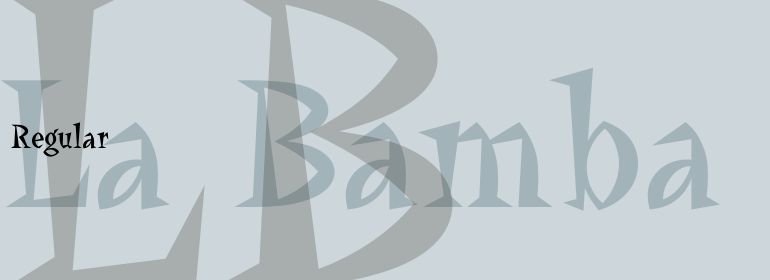
La Bamba™
La Bamba是英国设计师David Quay的作品,它深受20世纪50年代风格的影响。它具有完整的大写字母和小写字母以及一组装饰性的大写字母,以增加多样性。La Bamba是一个比较随意的设计,带有楔形衬线而且还散发着一种轻松、愉快的心情。
La Bamba is the work of British designer David Quay and heavily influenced by the style of the 1950s. It comes with complete upper and lowercase alphabets as well as a set of decorated initialling capitals for added variety. La Bamba is a casual design with wedge-shaped serifs and radiates a gay, light-hearted mood.